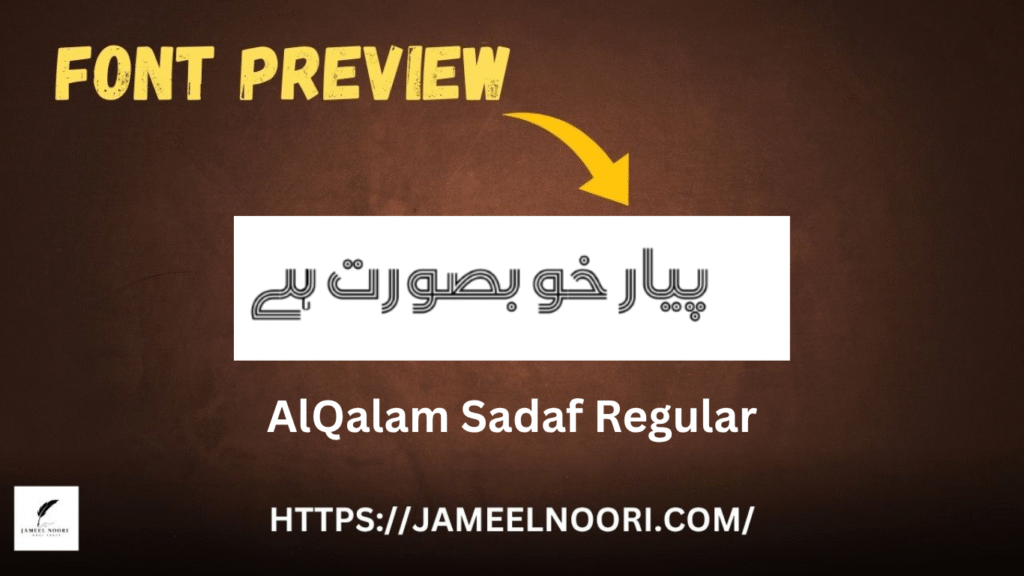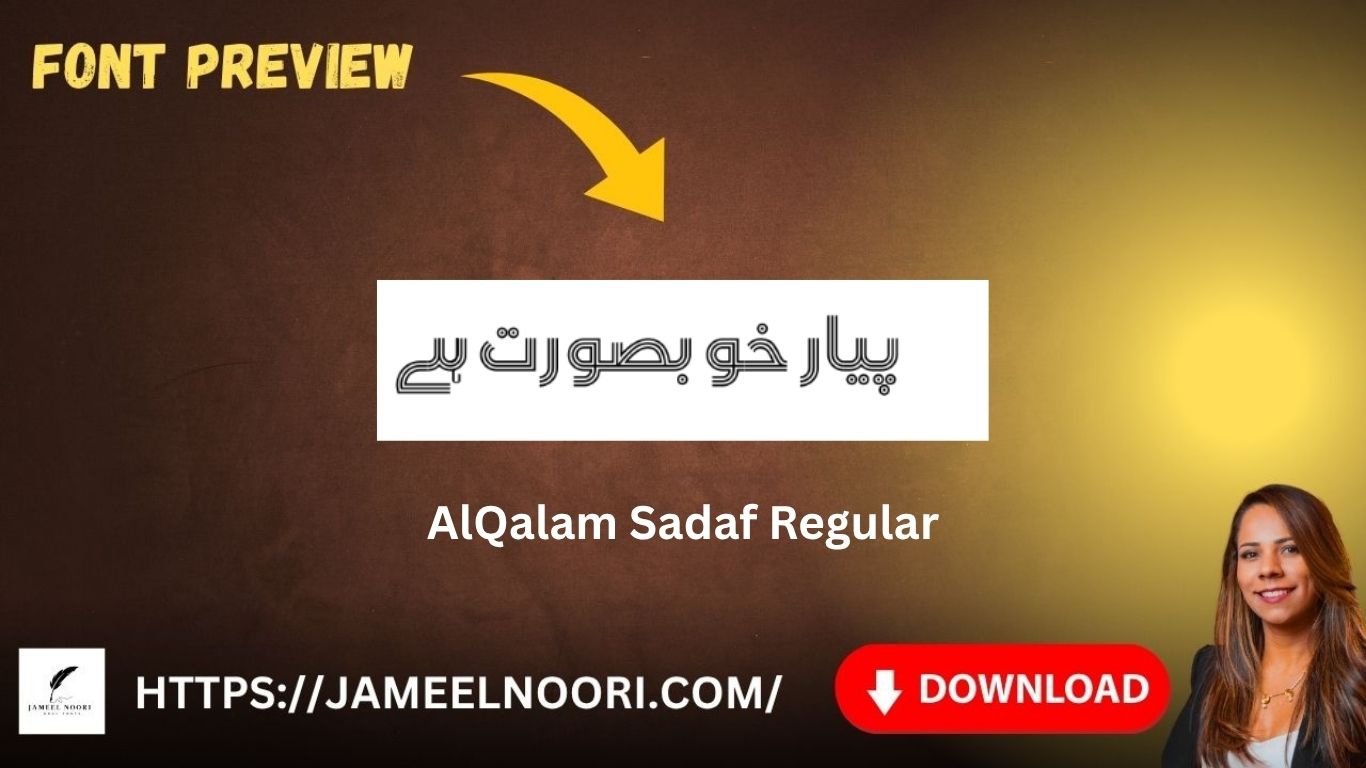
Urdu Font AlQalam Sadaf aik bohot hi popular aur elegant Urdu font hai jo specially un users ke liye design kiya gaya hai jo apne design aur writing projects me professional touch lana chahte hain. Ye TrueType free font readability aur stylish look dono ka best combination provide karta hai.
What is Urdu Font AlQalam Sadaf?
Urdu Font AlQalam Sadaf aik regular TrueType font hai jise AlQalam Team ne design kiya. Is font ka unique style aur modern calligraphy usay designers aur writers ke liye ideal choice banata hai. Ye font un logon ke liye perfect hai jo Urdu typography, graphics design, aur digital content creation me professional look chahte hain.
Features of Urdu Font AlQalam Sadaf
Ye font apni readability aur elegance ki wajah se mashhoor hai. Neeche kuch major features diye gaye hain:
Key Highlights:
- Stylish and professional design suitable for all uses
Why Choose Urdu Font AlQalam Sadaf?
Urdu Font AlQalam Sadaf ka style aur alignment isay doosre Urdu fonts se alag banata hai. Ye stylish font headings, titles aur design posters ke liye perfect hai. Kuch major reasons:
- Readable aur clear TrueType font
- Compatible with Lahore, Karachi, Islamabad based Urdu publication designs
- Free font hone ke bawajood professional quality
Best Use Cases of AlQalam Sadaf Urdu Font
- Graphic design posters
- YouTube thumbnails aur Urdu captions
- Social media posts (Facebook, Instagram, etc.)
- Book covers aur digital magazines
- Website headings aur blog titles
Conclusion – The Ultimate Urdu Font Choice
Agar aap Urdu writing me elegance aur simplicity chahte hain to Urdu Font AlQalam Sadaf aapke liye best choice hai. Iska TrueType format aur smooth curves likhai ko natural aur professional banate hain. Download karein aur apne next Urdu project me is stylish font ka best use karein.
What makes this font unique?
Its stylish curves and elegant Urdu script design.
Who designed the font?
It was created by the AlQalam Team.